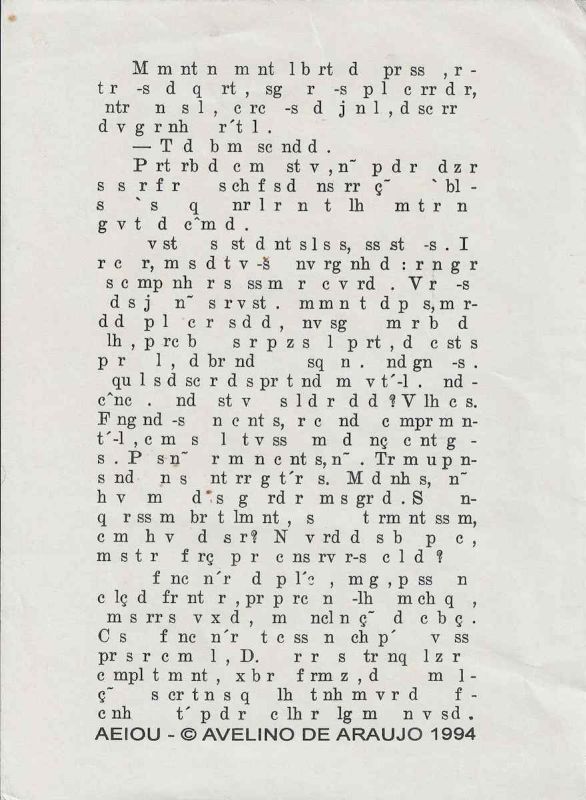
AEIOU é uma impressão gráfica de Avelino de Araújo realizada em 1994, vinculada à poesia visual, à poesia experimental, à arte conceitual, à tipografia e às investigações intersígnicas relacionadas ao campo do Poema Processo.
AEIOU é uma impressão gráfica de Avelino de Araújo realizada em 1994, vinculada à poesia visual, à poesia experimental, à arte conceitual, à tipografia e às investigações intersígnicas relacionadas ao campo do Poema Processo. A composição apresenta um extenso bloco textual construído quase exclusivamente por consoantes, sinais de pontuação, acentos e espaços, enquanto as vogais parecem ter sido retiradas das palavras. O título AEIOU, formado pela sequência tradicional das cinco vogais, identifica precisamente os elementos ausentes do corpo principal do texto. Avelino de Araújo transforma a supressão das vogais em procedimento poético e visual, criando uma escrita parcialmente legível, fragmentada e aberta à reconstrução mental do leitor. A obra mantém a aparência de um texto em prosa, com linhas, parágrafos, vírgulas, pontos, interrogações e outros sinais que preservam o ritmo e a organização sintática, embora o conteúdo verbal não possa ser lido de maneira imediata. A ausência das vogais compromete a fluidez da leitura, mas permite reconhecer estruturas, extensões de palavras e possíveis padrões da língua portuguesa. O leitor é convidado a completar mentalmente os intervalos e a participar da produção do sentido. O título pode ser entendido como índice, chave de leitura, inventário do que foi removido e declaração do método utilizado. A obra explora as relações entre presença e ausência, som e silêncio, escrita e leitura, código e decifração, informação e incompletude. As vogais, fundamentais para a formação sonora das palavras, aparecem apenas no título final, enquanto sua retirada transforma o texto em uma espécie de esqueleto consonantal. O resultado pode ser compreendido como linguagem privada, documento censurado, mensagem interrompida, texto econômico ou exercício de redução estrutural. A composição também sugere uma reflexão sobre censura, apagamento, falha de comunicação e perda de elementos essenciais da linguagem. Avelino de Araújo demonstra que a escrita continua visualmente reconhecível mesmo quando parte de seu sistema é retirada. A leitura deixa de ser apenas recepção e torna se operação de memória, hipótese e reconstrução. Na parte inferior encontram se a identificação AEIOU, o símbolo de autoria, o nome Avelino de Araújo e o ano 1994. AEIOU integra a produção do artista dedicada à transformação de letras, palavras, códigos linguísticos e processos de leitura em matéria poética e visual. Palavras chave para indexação: Avelino de Araújo, AEIOU, 1994, impressão gráfica, poesia visual brasileira, poema visual, poesia experimental, arte conceitual, Poema Processo, vogais, consoantes, supressão das vogais, texto sem vogais, linguagem incompleta, escrita codificada, leitura participativa, apagamento linguístico, censura, silêncio, tipografia experimental, palavra imagem, texto imagem, semiótica, intersigno, comunicação visual, arte gráfica brasileira, múltiplo gráfico, arquivo de poesia visual, arte brasileira do século vinte.TEXT FOR THE SALSA PROGRAM IN ENGLISH: AEIOU is a graphic print by Avelino de Araújo produced in 1994 and associated with visual poetry, experimental poetry, conceptual art, typography and intersemiotic investigations related to the field of the Poema Processo movement. The composition presents an extensive textual block constructed almost entirely from consonants, punctuation marks, accents and spaces, while the vowels appear to have been removed from the words. The title AEIOU, formed by the traditional sequence of the five vowels, precisely identifies the elements absent from the main body of the text. Avelino de Araújo transforms the suppression of vowels into a poetic and visual procedure, creating writing that is partially legible, fragmented and open to mental reconstruction by the reader. The work preserves the appearance of prose, with lines, paragraphs, commas, periods, questions and other signs maintaining rhythm and syntactic organization, although the verbal content cannot be read immediately. The absence of vowels disrupts reading fluency but still allows recognition of structures, word lengths and possible patterns of the Portuguese language. The reader is invited to complete the intervals mentally and participate in the production of meaning. The title may be understood as an index, reading key, inventory of what has been removed and declaration of the method used. The work explores relationships between presence and absence, sound and silence, writing and reading, code and decipherment, information and incompleteness. Vowels, which are fundamental to the sound structure of words, appear only in the final title, while their removal transforms the text into a consonantal skeleton. The result may be understood as a private language, censored document, interrupted message, economical text or exercise in structural reduction. The composition also suggests a reflection on censorship, erasure, communication failure and the loss of essential elements of language. Avelino de Araújo demonstrates that writing remains visually recognizable even when part of its system has been removed. Reading ceases to be only reception and becomes an operation of memory, hypothesis and reconstruction. The lower section contains the identification AEIOU, the authorship symbol, the name Avelino de Araújo and the year 1994. AEIOU belongs to the artist
Impressão gráfica em tinta preta sobre papel claro, composta por um grande bloco de texto alinhado verticalmente na região central da folha. As linhas apresentam sequências de consoantes, espaços, vírgulas, pontos, sinais de interrogação, acentos, cedilhas e outros elementos gráficos. As vogais não aparecem no corpo principal da composição, produzindo palavras incompletas e leitura descontínua. A estrutura mantém aparência de texto datilografado ou impresso, com margens irregulares, linhas de diferentes extensões e separações que sugerem parágrafos. Algumas letras maiúsculas aparecem no início de períodos ou trechos, reforçando a permanência de convenções da escrita. Na parte inferior encontra se a inscrição AEIOU, seguida pelo símbolo de autoria, pelo nome AVELINO DE ARAUJO e pelo ano 1994. O contraste entre o título completo e o texto privado de vogais constitui o principal procedimento visual e conceitual da obra. O suporte apresenta ondulações, vincos, pequenas manchas, alterações de tonalidade, marcas de dobra e sinais de envelhecimento e manuseio. A peça pode ser classificada como poema visual, impressão de artista, múltiplo gráfico, texto experimental, escrita codificada e documento conceitual, sendo relevante para pesquisas sobre Avelino de Araújo, Poema Processo, poesia visual, linguagem, vogais, tipografia, censura, leitura, semiótica e produção gráfica brasileira.OBSERVATION TEXT IN ENGLISH: Graphic print in black ink on light colored paper composed of a large textual block arranged vertically in the central region of the sheet. The lines contain sequences of consonants, spaces, commas, periods, question marks, accents, cedillas and other graphic elements. Vowels do not appear in the main body of the composition, producing incomplete words and discontinuous reading. The structure retains the appearance of typed or printed text, with irregular margins, lines of different lengths and separations suggesting paragraphs. Some capital letters appear at the beginning of sentences or sections, reinforcing the persistence of writing conventions. The lower section contains the inscription AEIOU, followed by the authorship symbol, the name AVELINO DE ARAUJO and the year 1994. The contrast between the complete title and the text deprived of vowels constitutes the principal visual and conceptual procedure of the work. The support presents undulations, creases, small stains, changes in tone, fold marks and signs of aging and handling. The piece may be classified as a visual poem, artist print, graphic multiple, experimental text, coded writing and conceptual document, making it relevant to research on Avelino de Araújo, Poema Processo, visual poetry, language, vowels, typography, censorship, reading, semiotics and Brazilian graphic production.
AEIOU is a graphic print by Avelino de Araújo produced in 1994 and associated with visual poetry, experimental poetry, conceptual art, typography and intersemiotic investigations related to the field of the Poema Processo movement.